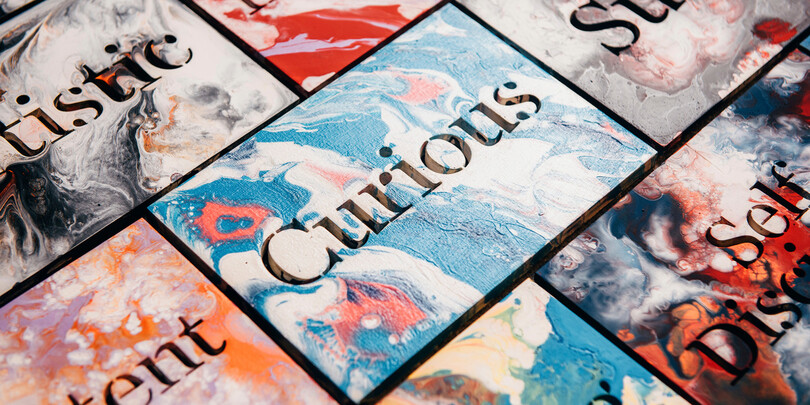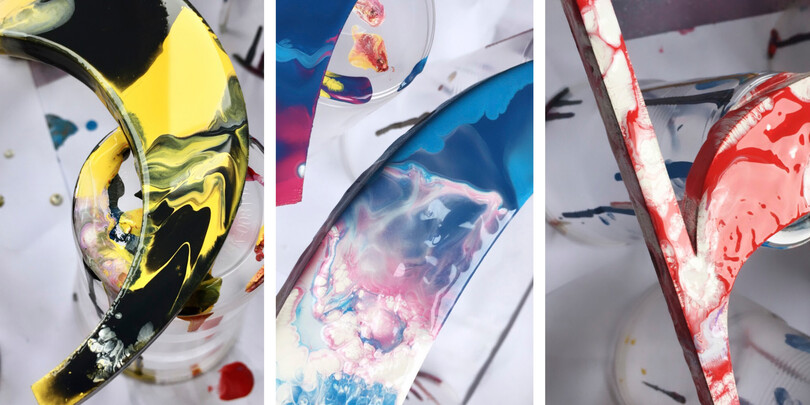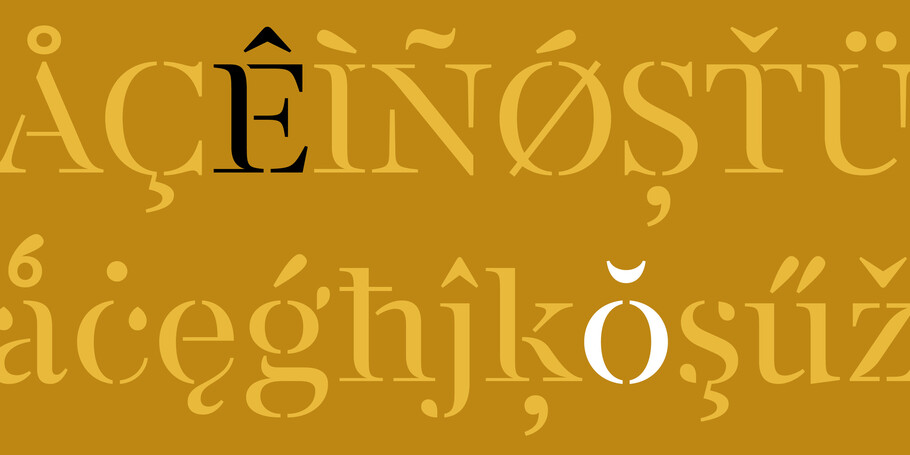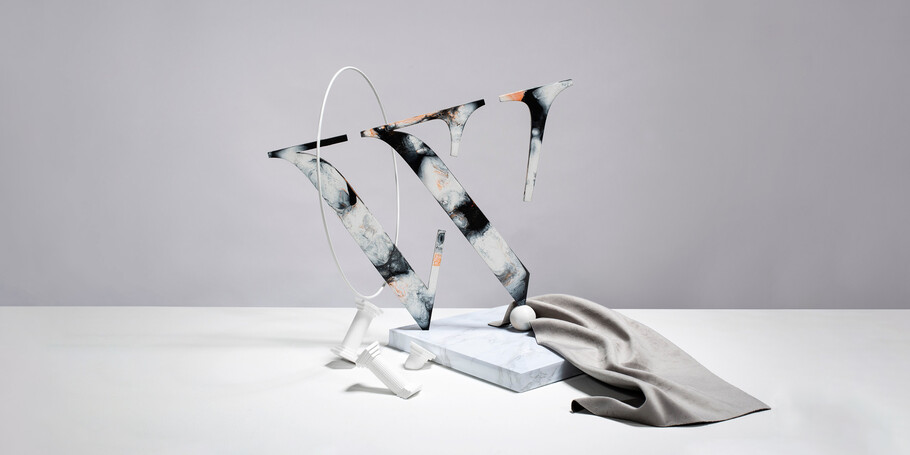
Los entresijos de la creación de FS Renaissance, con Craig Black y Pedro Arilla.
« Cada una de ellas es una obra de arte en sí, y tanto su elegancia como su belleza no precisan de las demás. »
Craig Black.
FS Renaissance es una fuente display hecha a mano en la que cada letra es una obra de arte, y juntas conforman una tipografía y un diseño armoniosos y con equilibrio técnico. La fuente es una colaboración entre Craig Black, el conocido diseñador gráfico y artista de lettering, y el director creativo de tipografía de Monotype, Pedro Arilla. El objetivo era estudiar la relación entre arte y diseño a través de la estrecha colaboración entre un artista y un diseñador tipográfico para equilibrar la belleza y la funcionalidad.
Hace poco, Craig y Pedro hablaron sobre sus puntos de vista acerca de los conceptos y el proceso creativo de FS Renaissance.
¿Cuál fue el concepto original del tipo de letra y cómo decidisteis qué dirección seguiría?
Craig: El término «hombre del Renacimiento» hace referencia a algunos de los artistas, inventores, científicos y pensadores con más talento que protagonizaron aquella época. Fue un momento de esplendor en las artes, las ciencias, el aprendizaje y la filosofía que tuvo lugar entre el siglo XIV y el XVI.
Siempre he admirado a los hombres y las mujeres de aquella época, y a qué nivel dominaban distintas disciplinas. Un ámbito que me fascina en particular es la escultura y el tallado de tipografía en piedra. El nivel de complejidad es increíble, y admiro la paciencia que debieron necesitar para crear una obra de arte tan bonita.
Todo eso me sirvió de inspiración para crear un tipo de letra que simbolizara ese nivel de admiración, combinándola con la influencia moderna de una tipografía con estarcido. Sabía que podíamos desarrollar todavía más este concepto y crear algo especial juntos.
Pedro, ¿qué sentiste al ver por primera vez el concepto de Craig?
Pedro: Fue un flechazo. Conocía bien el trabajo de Craig, y, aunque esperaba que me sorprendiera, no me imaginaba que fuera así. Era una tipografía elegante, pero con una seguridad en sí misma que solo podría ser obra de una persona con verdadero talento para las letras.
¿En qué medida evolucionó el diseño y por qué?
Pedro: El diseño original de Craig era muy bueno, pero hacerlo funcionar como sistema tipográfico no es tan sencillo. Tras el momento inicial de asombro, empecé a fijarme en los detalles. La idea principal estaba ahí y era muy sólida, pero todavía teníamos que hablar de cómo se crea un sistema, de proporciones, de equilibrio entre blancos y negros, y de todos esos detalles esenciales en el diseño.
Intentamos buscar una forma de hacerlo respetando el concepto original. Principalmente, fue cuestión de buscar la verdadera esencia de la obra de Craig y aplicarla a una base tipográfica. Diría que el diseño no evolucionó tanto, pero sí maduró y se asentó mucho.
Craig: Como ha dicho Pedro, el tipo de letra no evolucionó tanto con respecto a mis bocetos originales, pero sí que se le aportó algo de sutileza para que funcionara como sistema tipográfico. El nivel de dedicación de Pedro a su oficio y su atención a los detalles contribuyó enormemente al equilibrio y la fluidez de la tipografía.
¿Cómo fue vuestra colaboración? ¿Participó alguien más?
Craig: Creo firmemente en el poder de la colaboración, y trabajar con Pedro ha sido una de las mejores experiencias que he tenido. Los dos nos unimos para resolver las complicaciones que planteaba el tipo de letra. Yo creé los bocetos originales, pero le cedí las riendas a Pedro para que hiciera lo que tan bien sabe hacer y no me decepcionó. A medida que avanzó el proyecto, nuestra relación también evolucionó, lo que nos permitió colaborar mucho mejor y creó una plataforma más abierta para hablar sobre nuestras ideas y dificultades.
Pedro: En esencia, el proceso se basó en hablar con regularidad. A veces, ni siquiera hablábamos del proyecto, sino sobre diseño y arte en general. Craig confió en mí desde el principio, así que empecé a desarrollar un tipo de letra siguiendo su receta. En cuanto el conjunto de caracteres empezó a crecer, tuve que tomar cada vez más decisiones sobre diseño, así que seguimos en contacto. Siempre viene bien otro par de ojos a la hora de diseñar un tipo de letra, pero en este caso fue vital. Las sugerencias de Craig fueron siempre útiles y positivas.
¿Cómo describirías FS Renaissance?
Pedro: La base es una serif de transición, pero con un toque de estarcido. Desde un punto de vista más emocional, diría que es un tipo de letra display con unos contornos elegantes y una apariencia atemporal. Tiene un aire grandioso. En palabras de Napoleón: desde lo alto de estas formas de letras, cinco siglos de tipografía nos contemplan.
¿Cuáles son tus elementos favoritos del diseño?
Craig: Me gusta especialmente la sutileza de los detalles de las letras. Cada una de ellas es una obra de arte en sí, y tanto su elegancia como su belleza no precisan de las demás. Al combinarlas, se crea un fino equilibrio entre diseño y arte, algo de lo que estoy muy orgulloso.
Pedro: Estoy especialmente satisfecho con la textura. Aunque sea un tipo de letra display, la textura es importante, y hemos conseguido un buen equilibrio entre blancos y negros, elementos conectados y desconectados, y diseño y arte.
¿Por qué es diferente este tipo de letra del resto de las fuentes display del mercado?
Pedro: En mi opinión, la clave es la sencillez de la fórmula. No suelen gustarme los tipos de letras con estarcido, pero esta es diferente, ya que los cortes no son rígidos y parece que baila con la luz. Como resultado, es de una elegancia intrínseca y muy singular.
Craig: Estoy totalmente de acuerdo con Pedro en que la sencillez de la fórmula es lo que hace que funcione tan bien, aunque no comparto su opinión sobre el estarcido, ¡a mí me encantan! La combinación de formas empleada para crear cada letra da lugar a que sean obras de arte muy hermosas en sí mismas.
¿Para qué puede usarse?
Pedro: Títulos, pósteres, portadas… en cualquier lugar donde sea necesario mostrar elegancia y delicadeza, y expresar sofisticación y finura. Sin embargo, también vale para todo lo contrario, ya que FS Renaissance es una visión irreverente de los tipos de letras con estarcido, por lo que puede usarse como elemento de contraste en un diseño más brutalista.
MT_Fonts_FS_Renaissance_MTcom-Blog_2880x1440_003
¿Con qué otros tipos de letras funciona bien?
Pedro: Por ejemplo, para el cuerpo del texto quedaría bien con una sans o una serif. Sin embargo, su compañera ideal sería una sans geométrica para enfatizar esa sensación de pureza tipográfica.
¿Por qué se llama FS Renaissance?
Craig: Siempre me ha inspirado el genio de Leonardo da Vinci, un hombre que sobresalió en muchas disciplinas. Fue pintor, escultor, botánico, matemático y mucho más. Inventó prototipos de máquinas voladoras, estudió la anatomía humana y alcanzó una gran fama durante su vida que todavía pervive.
¿Qué hacía distinto a Da Vinci de otras personas? En parte, que era un genio absoluto. Sin embargo, el hecho de que profundizara incansablemente en sus intereses es lo que le permitió alcanzar tantos hitos en su vida y el motivo de que su legado como hombre del Renacimiento siga vivo.
Ese legado ha inspirado a las personas y a la forma de pensar actuales.
Hoy en día, ser una persona del Renacimiento no implica que tengas que dominar la poesía o la escultura. Significa abrirte al mundo tanto como sea posible y aprovechar todas las oportunidades que se presenten en tu camino. Significa cultivar la mente y el cuerpo, ya que la primera necesita que el segundo esté en buen estado para desplegar todo su potencial. Significa aprender tanto como puedas. Viajar y ver el mundo, conocer a su gente y aprender sus lenguas. No tener miedo de quién eres y encontrar la comodidad en tu propia piel.
Estas características influyen en mi propia naturaleza y quería reflejarlo mediante un tipo de letra.
¿Puedes hablar un poco de la idea sobre la que se sustenta el lanzamiento?
Craig: Me influyeron las pinturas, las esculturas y la arquitectura del periodo renacentista. Las formas y las combinaciones de colores funcionan muy bien juntas y crean un gran equilibrio. Me inspiré en eso a través de mi técnica de fusión de pintura acrílica. Quería representar ese periodo empleando mi propia interpretación de las esculturas tipográficas y la fusión de colores. Era importante combinar el mundo del diseño y el arte, y mostrar cómo pueden influir el uno en el otro, así que creé estas esculturas tipográficas como obras de arte en sí mismas.
Al contemplar el arte del Renacimiento, siempre me preguntaba cómo habían conseguido hacerlo. Especialmente, teniendo en cuenta el momento en el que se creó. Esta reflexión me hizo llegar a la idea de que las personas del Renacimiento iban muy adelantadas a su tiempo, así que quise representar ese tren de pensamiento mediante mi propio arte. Intenté hacer a mano todo lo que pude, al igual que en el periodo renacentista, para que la gente se preguntara por la composición de las esculturas tipográficas y cómo se habían creado.
Por ello, colaboré con la maravillosa Susan Castillo, que es una fotógrafa excepcional. Su estilo y la atención que presta a los detalles eran idóneos para este proyecto, y consiguió dar vida a esas reflexiones.
Entrevista con Craig Black y Pedro Arilla.